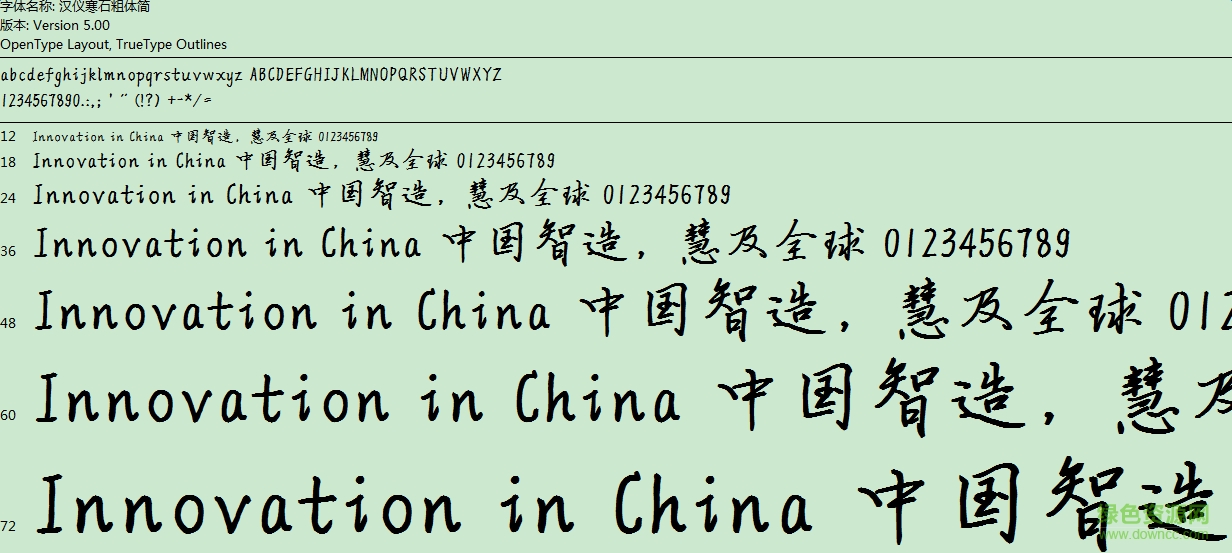
漢儀寒石粗體簡(jiǎn)
漢儀寒石粗體是漢儀系列的草書風(fēng)格字體軟件,筆畫看似放浪不羈,實(shí)則透露著作者無拘無束的瀟灑氣息,值得用戶收藏使用,歡迎大家來綠色資源網(wǎng)踴躍下載哦!
漢儀寒石粗體
小編點(diǎn)評(píng)
漢儀寒石粗體是一款手寫字體,用筆流暢,行云流水,字體落落大方,排版方面使用較為妥當(dāng)。